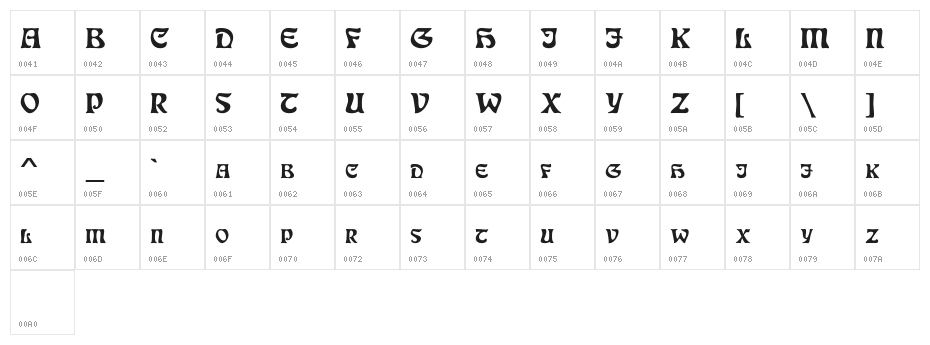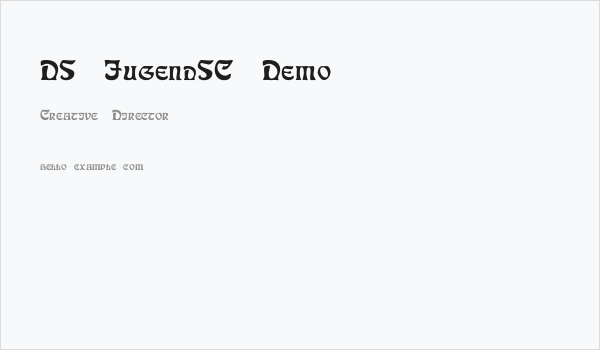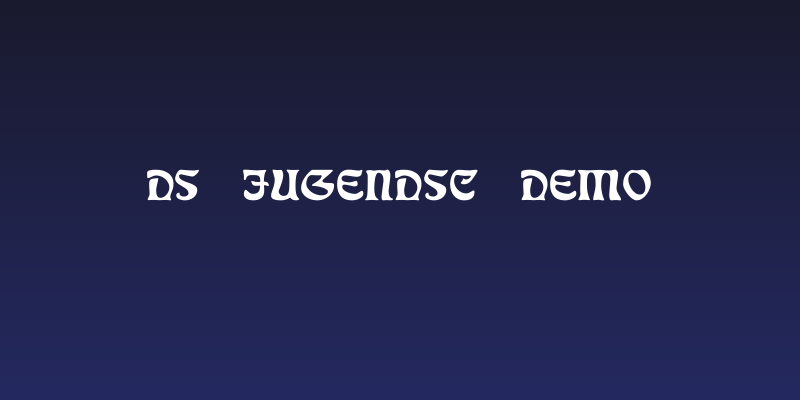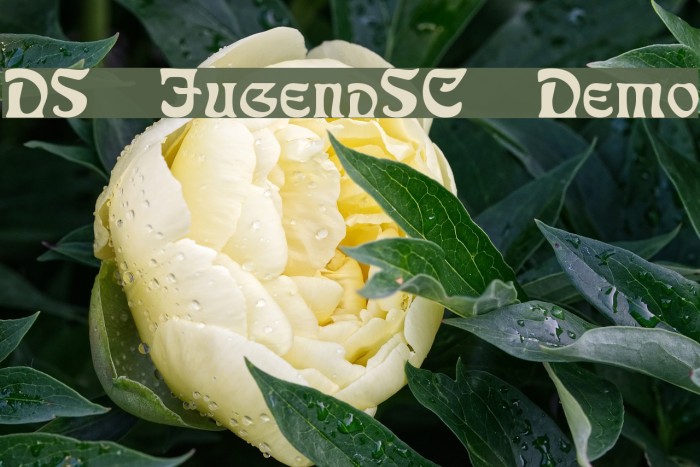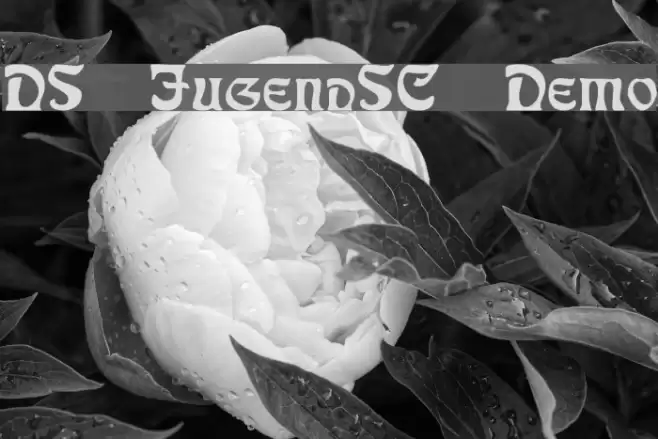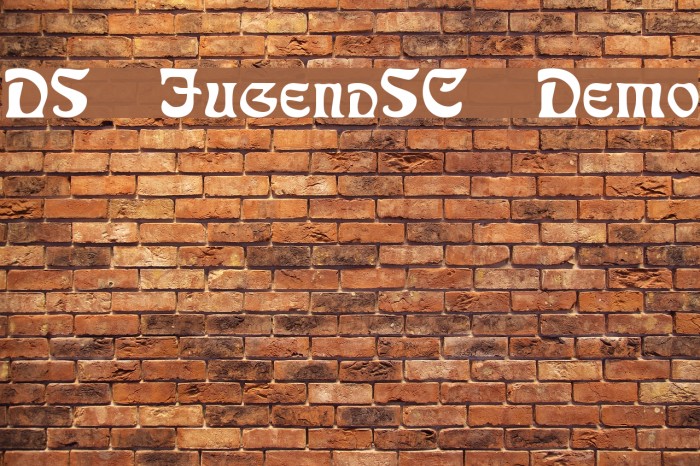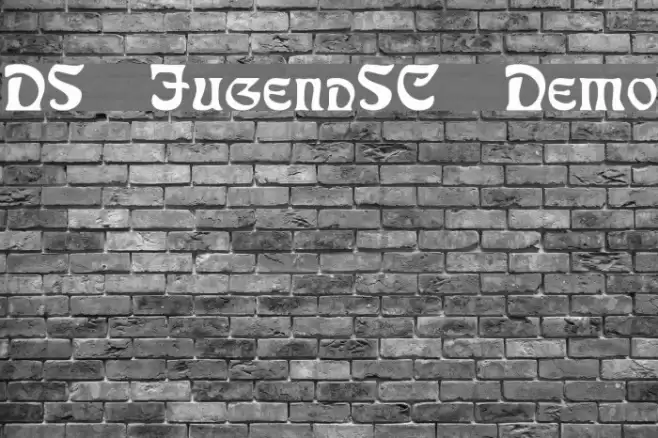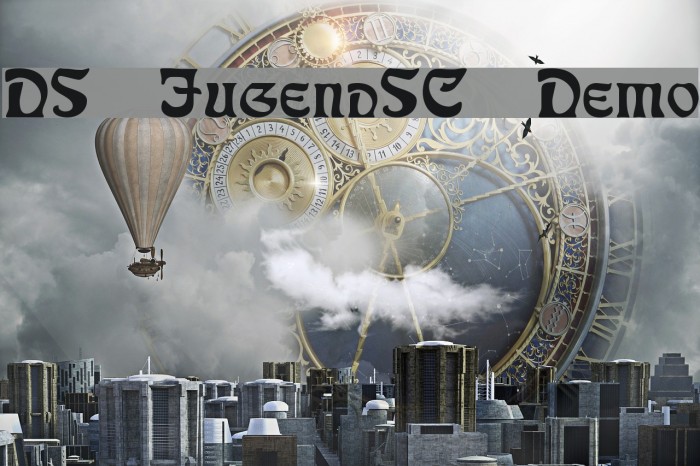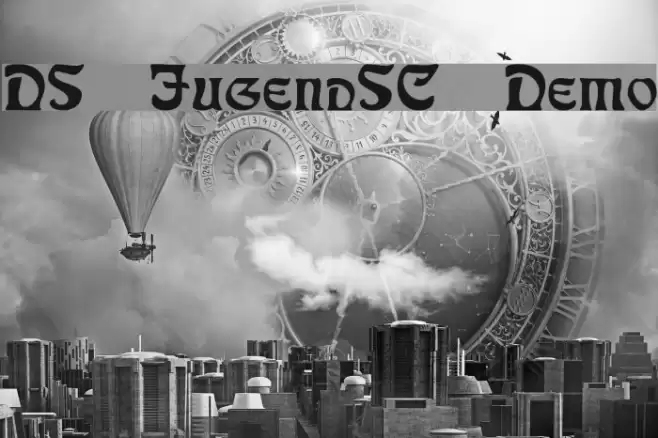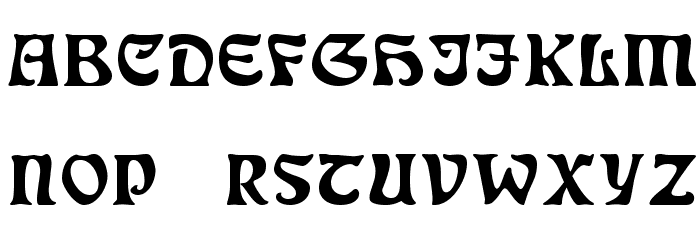
DS JugendSC Demo Font
| Vorgeschlagene Projekte | Ideal for projects requiring a historical or medieval theme, such as book covers, posters, or themed event invitations. |